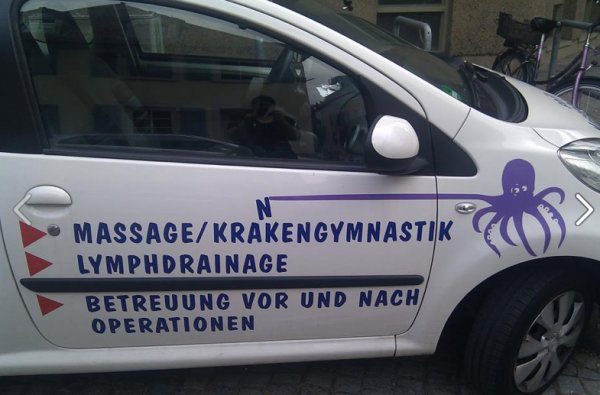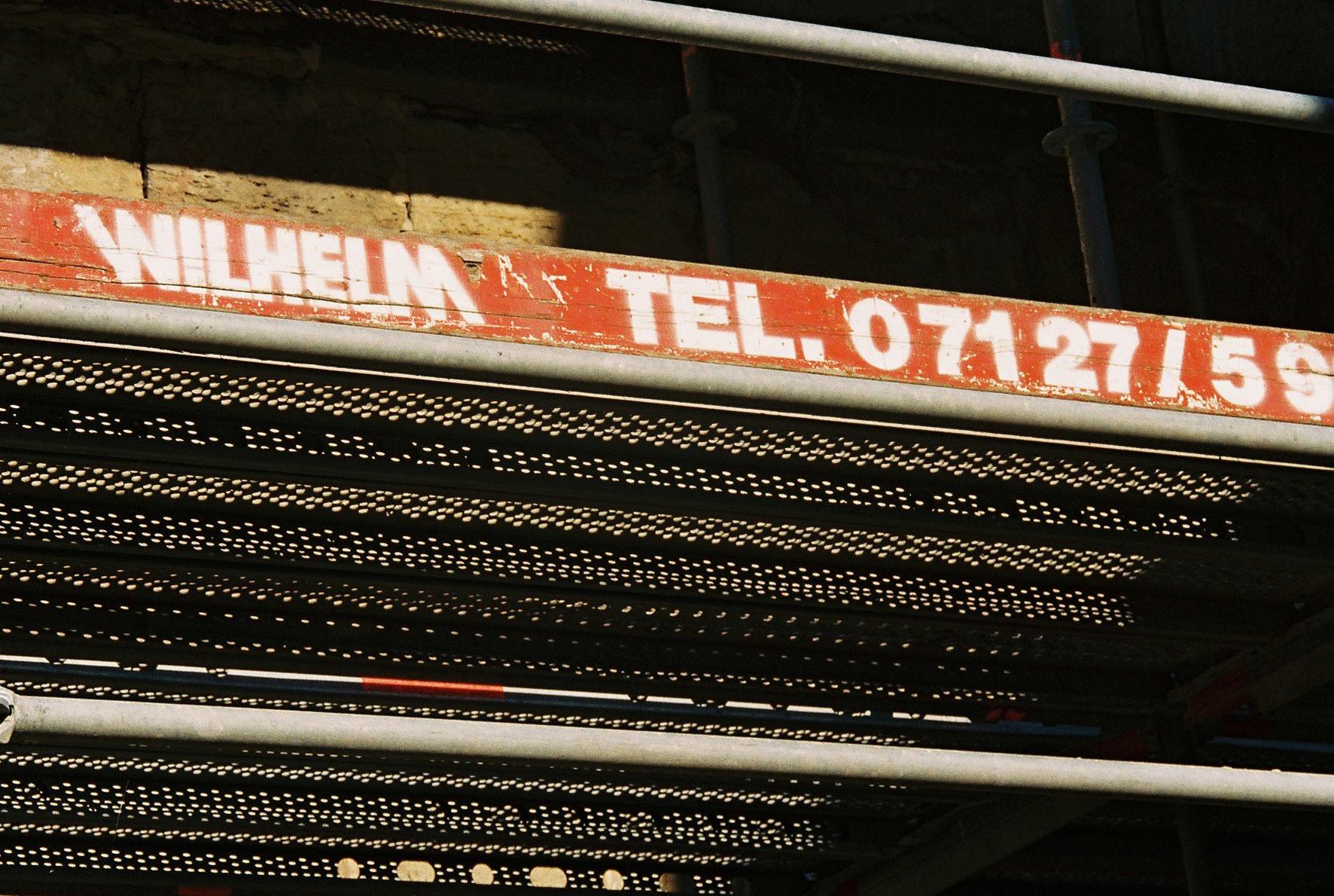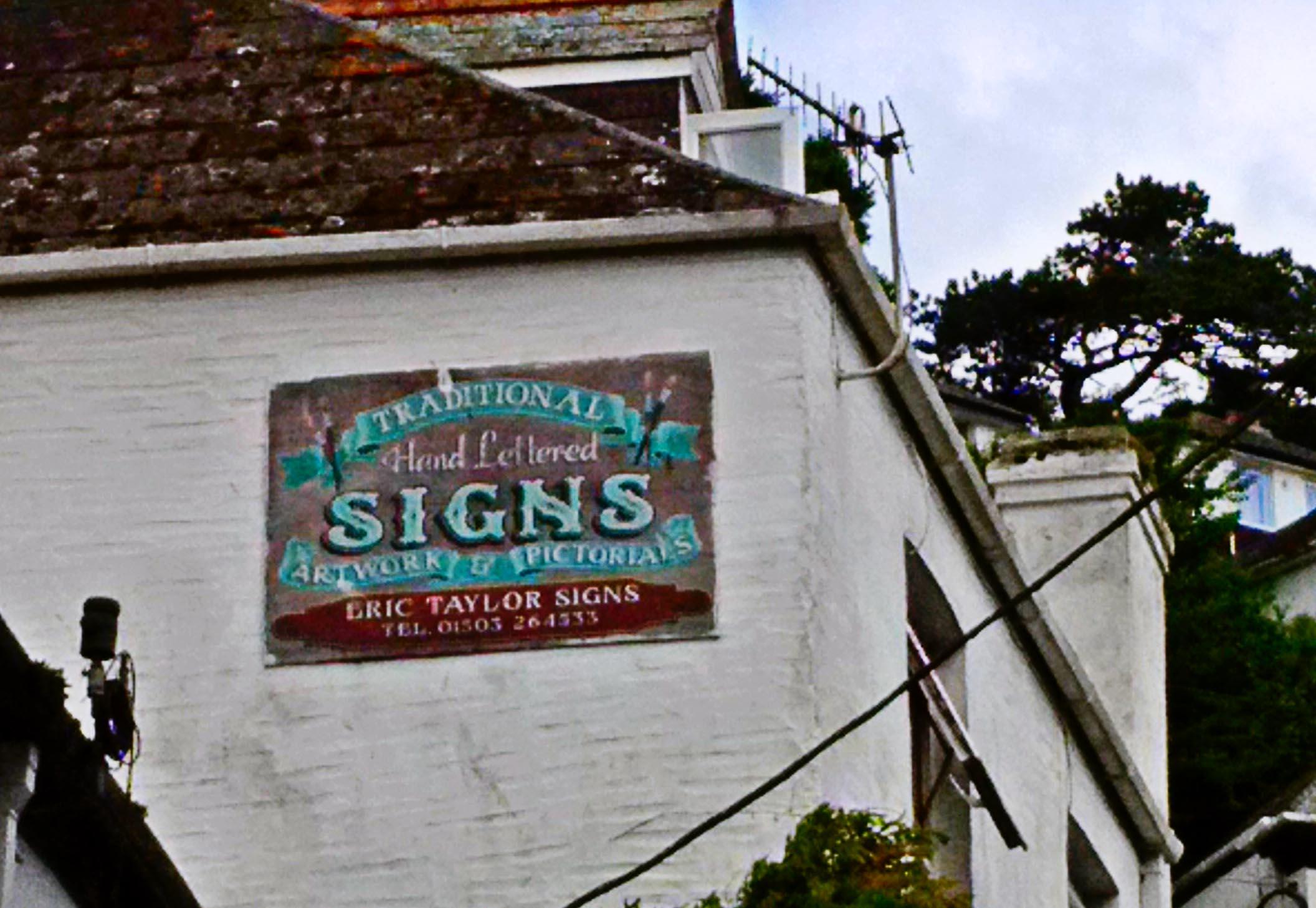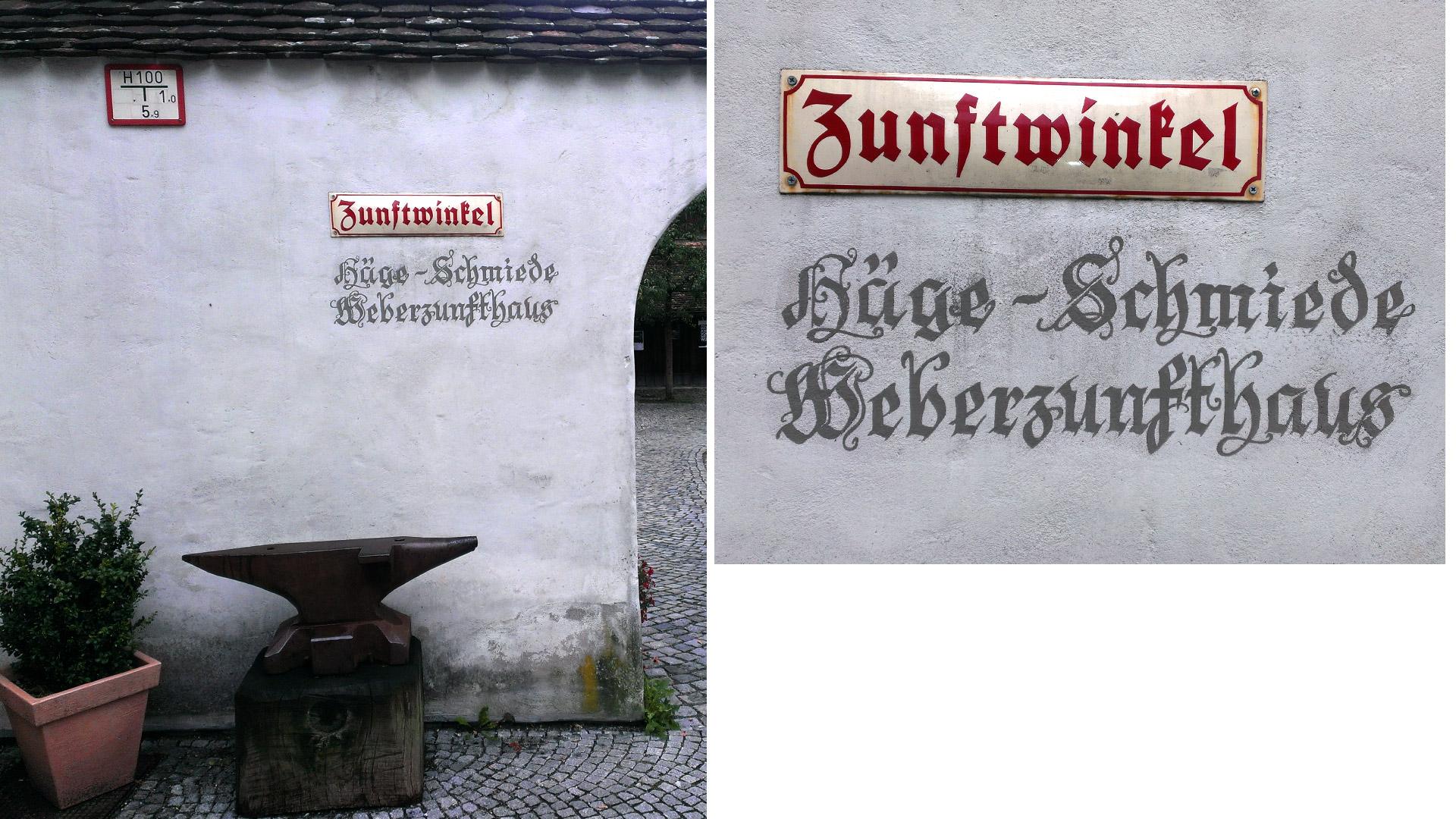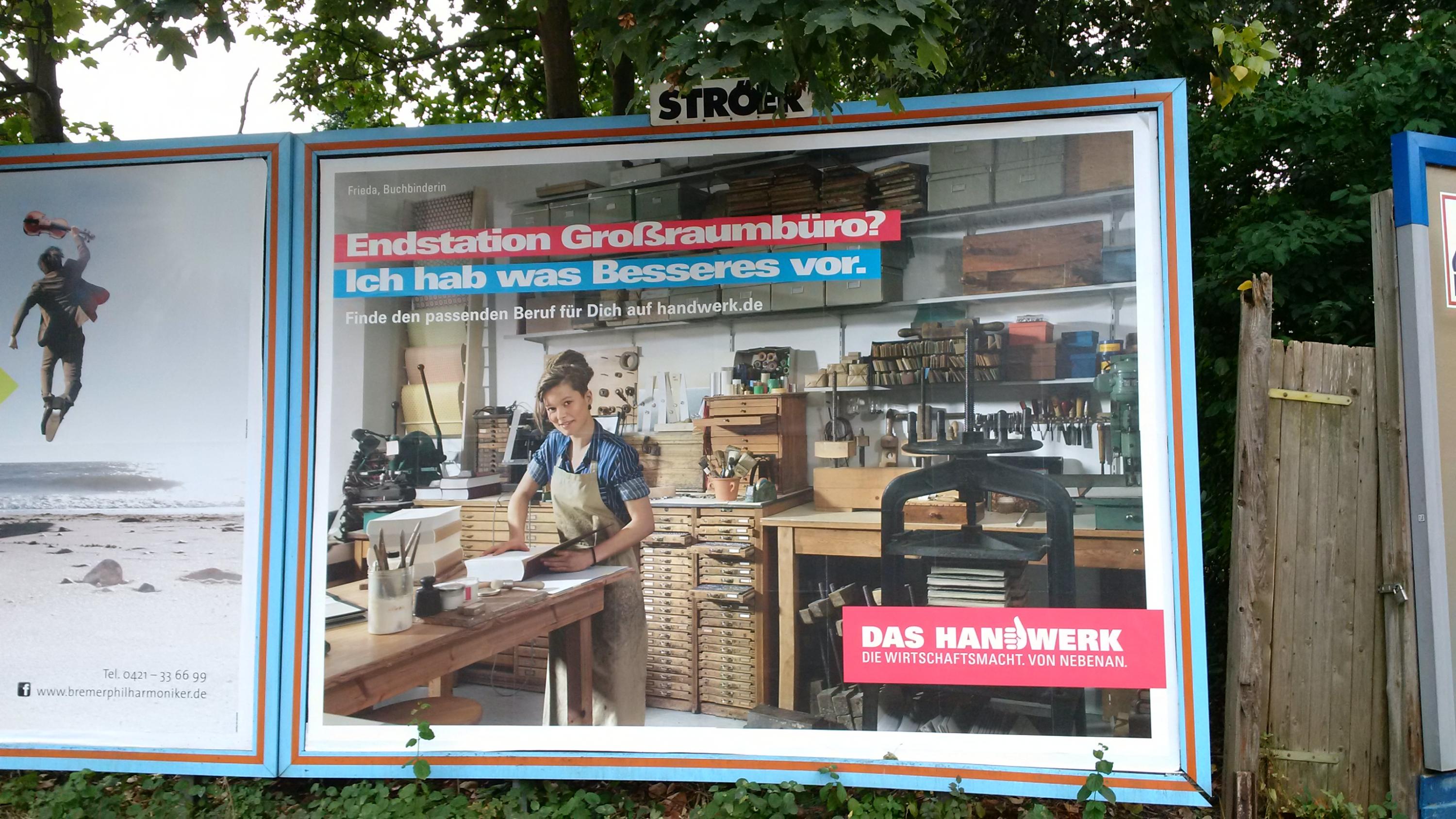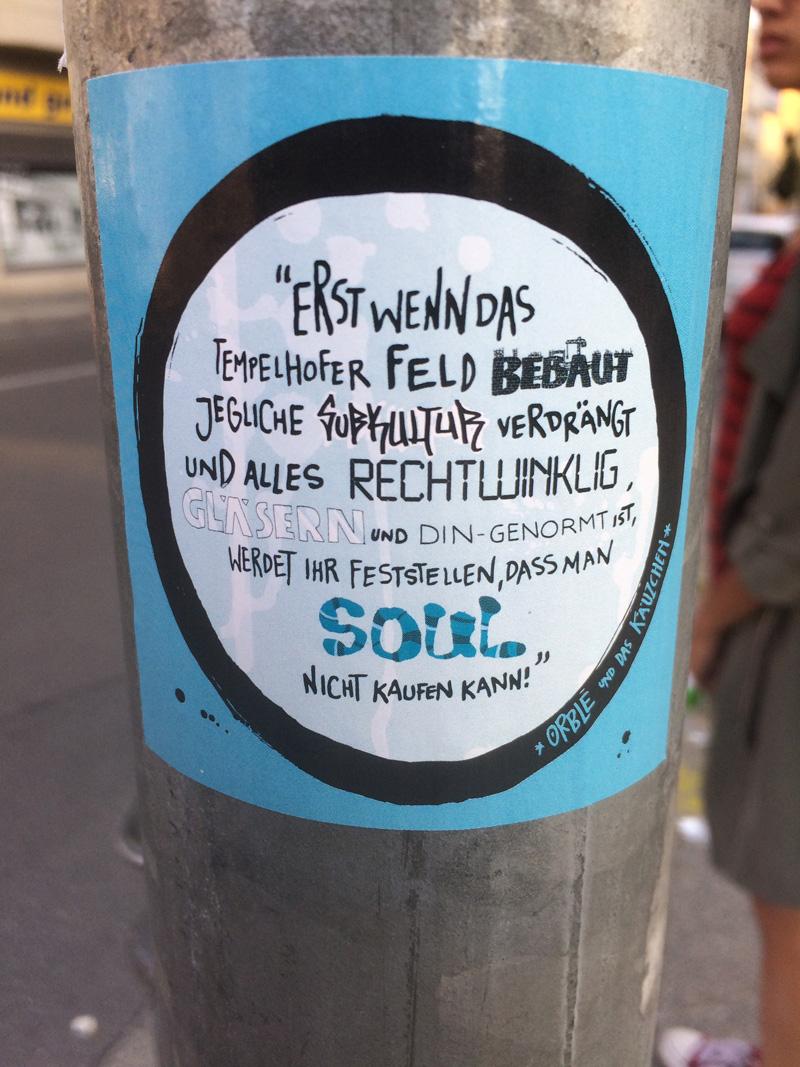
Ist nicht das beste Bild aus verschiedenen Gründen, aber ich fand’s ganz hübsch und wollte es Euch nicht vorenthalten. Gesehen in Polperro in Cornwall.
Gefunden in Wangen im Allgäu.
Mir gefällt die Schrift, also nicht das Schild, sondern das Gemalte darunter sehr gut. Überhaupt gefällt mir der ganze Eingang :-)
Ich fürchte dieses Zitat gab das Theaterstück nicht her ;-)
Die bepinsel ich aber nicht – wobei: das wäre ein schön kontinuierlicher Job, da es nach jedem Schnippeln neu muss :cheer::-|
Allerdings würde mich schon interessieren, ob die LED-Technik schon ausgereift genug ist, um solche Konstrukte schick flächig zu beleuchten. So eine leuchtende 28 aus der Hecke heraus hätte schon was!
Bestimmt haben die unter der 28 rote und blaue LEDs entsprechend angeordnet, damit nach dem Heckenschnitt diese Hausnummer entsprechend stärker wächst.
Gerade in Bremen gesehen. Auch wenn sich den Profis ob des Misch-Maschs vermutlich der Magen umdrehen wird fand ich es ja doch interessant daß jemand entschieden hat daß die Werkstatt Werbewirksam ist, also vom Publikum verstanden wird.